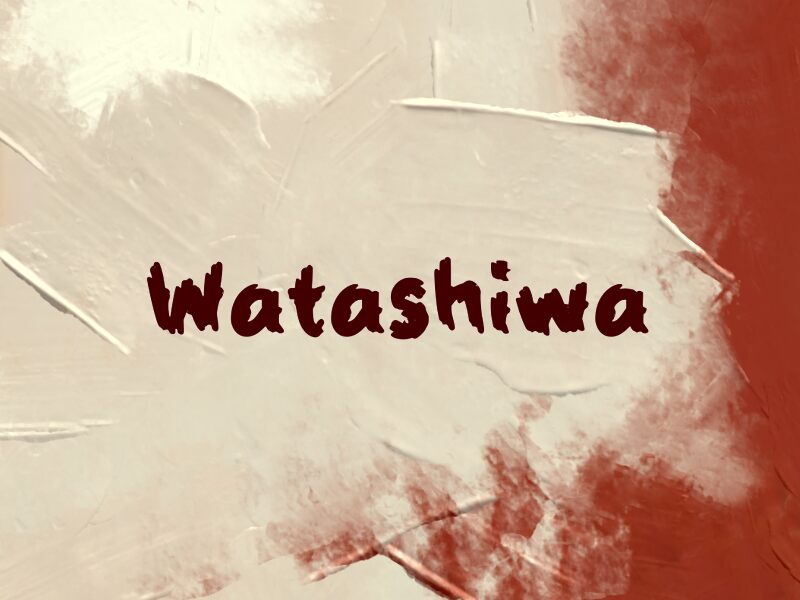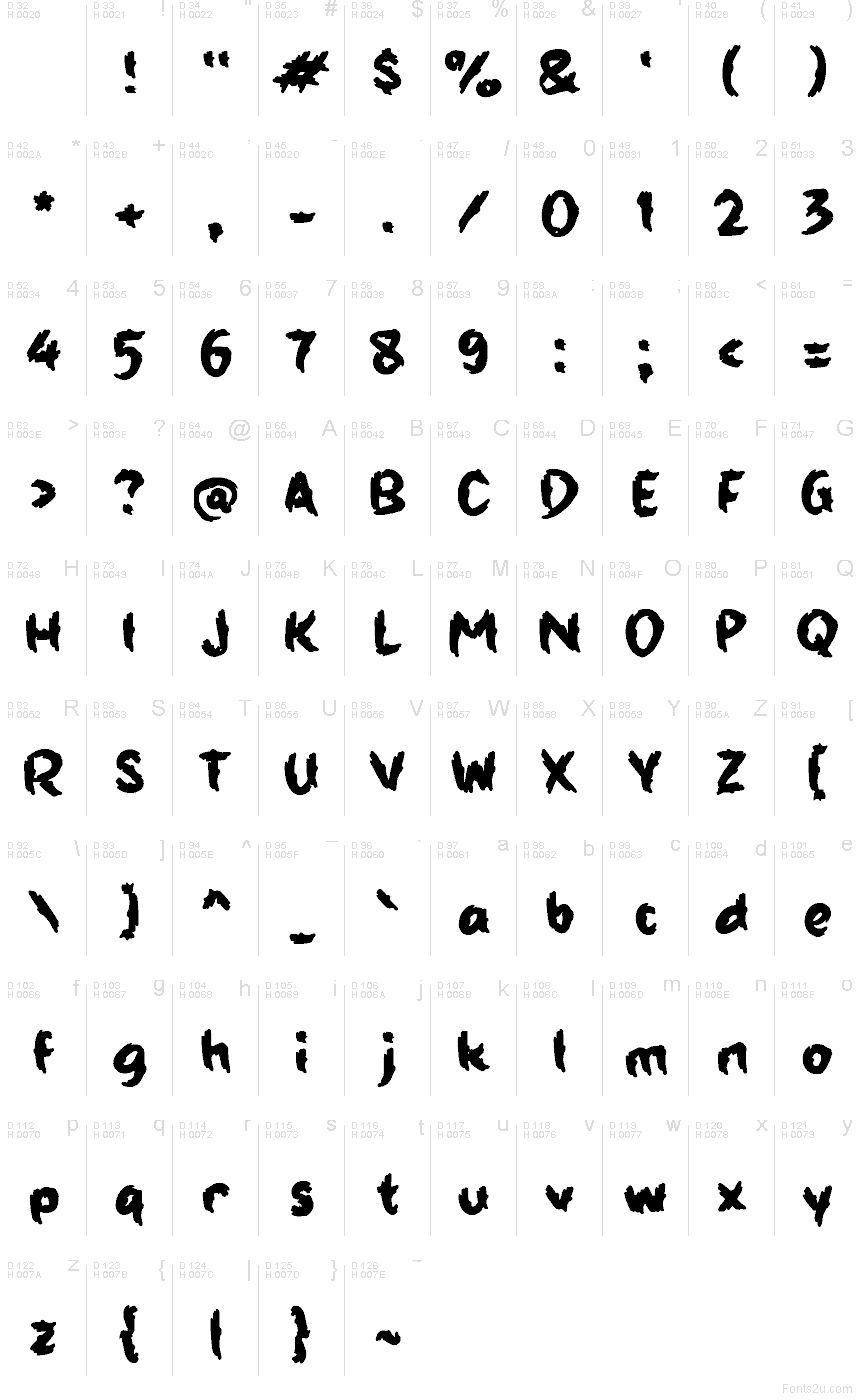
Watashiwa od Wep to darmowy krój pisma typu brush, pełen zabawy i ręcznie malowanego charakteru. Litery są grube, miękkie i nieco niepokorne – zaokrąglone kształty, postrzępione krawędzie i wyraziste cięcia sprawiają, że cały font wydaje się szybki i ludzki, a nie wygładzony.
Świetnie pasuje do nagłówków plakatów, brandingu kawiarni, ulotek muzycznych, grafik na naklejki czy luźnych opakowań, gdzie liczy się żywy akcent, a nie surowy porządek. Jako darmowy font, doskonale sprawdza się też w krótkich promocjach w social mediach, na planszach tytułowych czy nazwach na merch, ponieważ te masywne, malarskie kształty zachowują swoją energię nawet w jednym czy dwóch słowach.
Watashiwa
Prezentacja i próbka wizualna czcionki Watashiwa
Mapa znaków czcionki Watashiwa
Mapa znaków czcionki Watashiwa: Podstawowy łaciński, strona 1
Glify czcionki Watashiwa — Podstawowy łaciński, strona 1